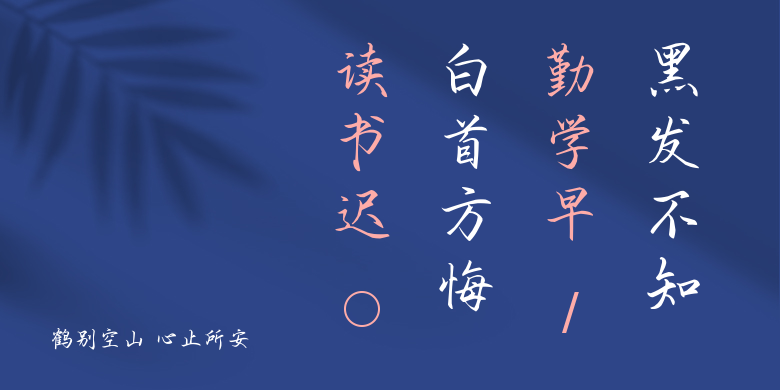
鹤别空山 心止所安
鹤别空山 心止所安,这款字体结构工整、笔画清晰,兼顾美观与易读性,适用于标题、正文、海报、包装、LOGO 等多种场景。字形优雅稳定,风格百搭耐看,适配日常排版与创意设计,让文字呈现更舒适、更具质感。鹤别空山 心止所安一笔一画,皆是细节,以均衡的比例、流畅的线条打造舒适视觉体验,字形端正大气,风格简约现代。无论是商业设计、品牌宣传还是日常排版,都能轻松驾驭,让文字更有格调与力量。鹤别空山 心止所安字体下载。